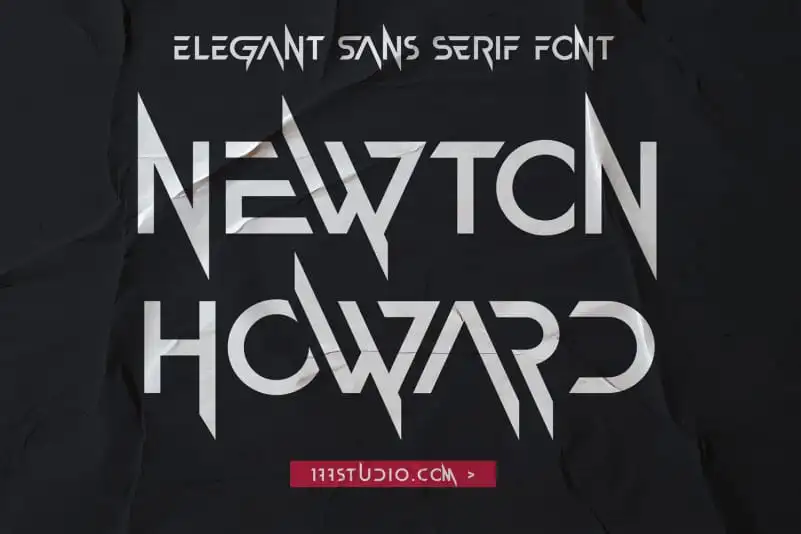
Newton Howard Font – Download Grátis
Nova Iorque está sempre a dar passos na direção da futurismo, inspirando novas tendências culturais e tecnológicas. O Newton Howard Font é uma ótima escolha para quem procura um estilo moderno e futurista. Este font de tipo grego oferece uma aparência geometricamente perfeita, com pontas redondas e ângulos retos que criam um aspecto técnico e tecnológico ideal. Esta fonte abrange uma ampla gama de recursos do OpenType, tornando-a perfeitamente adequada para desafios de design gráfico variados como webdesign, embalagem, criação de logotipos, entre outros. O Newton Howard Font é um ativo imprescindível para aqueles que buscam uma fonte futurista e tecnológica em sua próxima peça de design. Englobe a essência da Nova Iorque moderna com este tipo de fonte, ele certamente dará o tom perfeito a seu projeto.